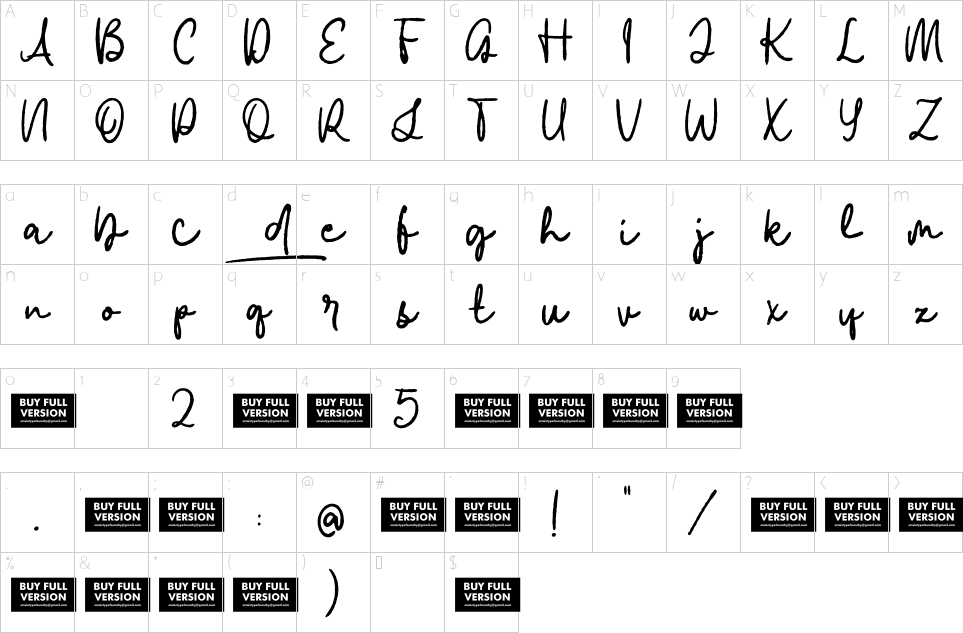
Blowing Trumpet Font – Download Grátis
Descubra a atmosfera envolvente e natural desta fonte chamada “Blowing Trumpet”. Conhecida por seu brado forte e vibrante, esta fonte oferece uma experiência visual única para seus projetos. Desenvolvida pela Anxietype Foundry, esta fonte é uma escolha atraente tanto para design gráfico quanto para o layout do site. Com um download total de 295 vezes em sua categoria de fontes gratuitas, ela é uma opção popular entre designers e desenvolvedores que buscam uma paleta vibrante e moderna. Adquira-a hoje e explore como essa fonte pode transformar seus projetos digitais na tela do seu dispositivo.